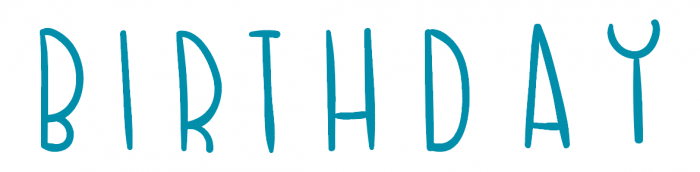
Suche die abgebildete Schrift: handgeschrieben, asymetrisch in der Höhe
ich suche die handgeschriebene Schrift um eine Headline zu vervollständigen. Würde mich freuen, wenn jemand helfen kann. Vielen Dank vorab!